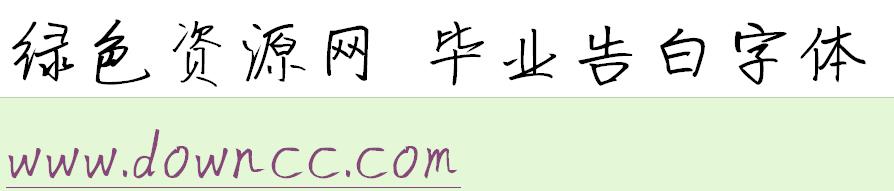
毕业告白字体ttf这款字体在情书体中十分受欢迎,每一个字体都拥有浓厚的情书告白意味,十分不错,在用户使用的时候能够让你感受到情书告白般的乐趣,在与小伙伴们之间进行交流的时候使用这款字体将更加不错!
这款字体是小编搜集的情书体中比较不错的字体了,正如每一个人都有一个想要在毕业时告白的女神一样,这款字体将带给你不错的告白悸动。
这款字体在使用的时候将能够很好的达到用户所需的字体显示效果
在众多的情书体中这款字体将占据不错的地位,拥有十分精美的行文结构,精美异常